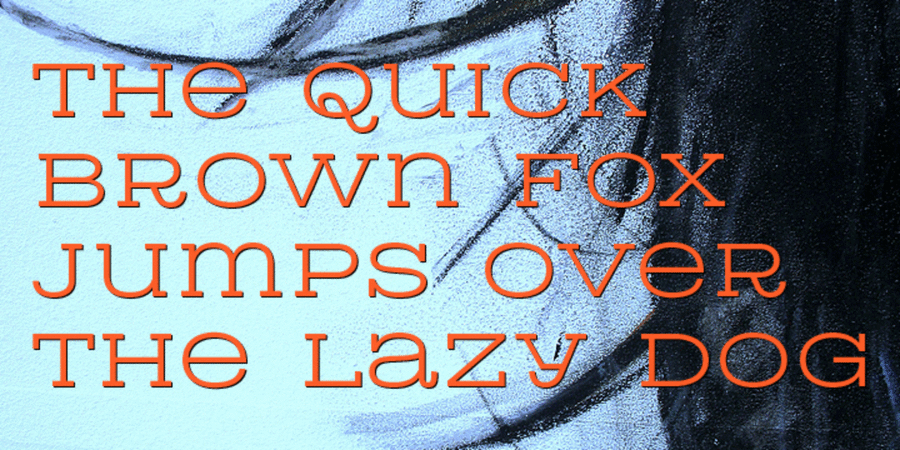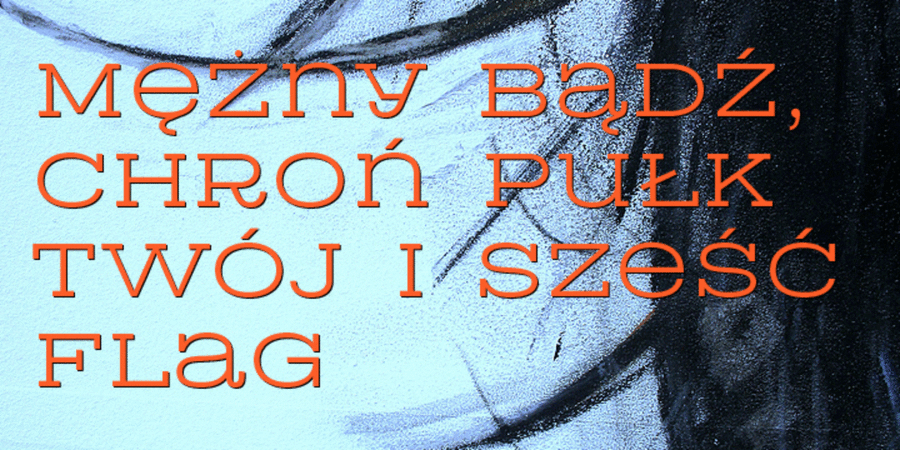
Шрифт в стиле ковбойских родео для заголовков и плакатов. Разработан Сергеем Ткаченко в 2011 году.
Асоціації з сімейством шрифтів Rodeqa Slab 4FОсобистість і характер гарнітури:
хіпстерський, традиційний, стійкий, якісний, добротний, чіткий, самостійний, західний, статичний, рівний, твердий, дерев'яний, просторий, ремісничий, крафтовий, гучний, переконливий, яскравий, помітний, серйозний, ковбойський, мотивуючий, мачо, амбітний, бандитський, вінтажний, кінематографічний, значний, важкий, авторитетний